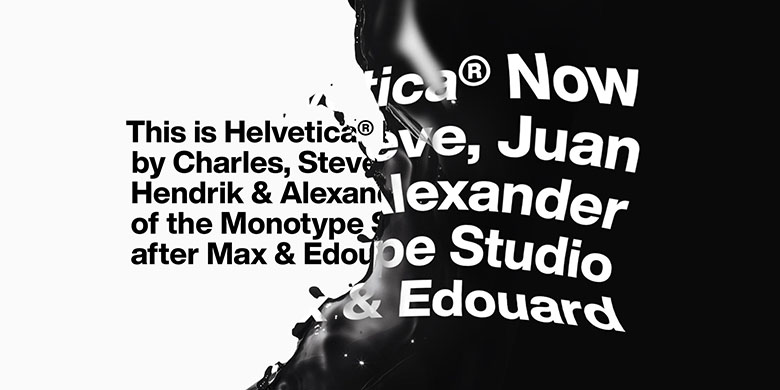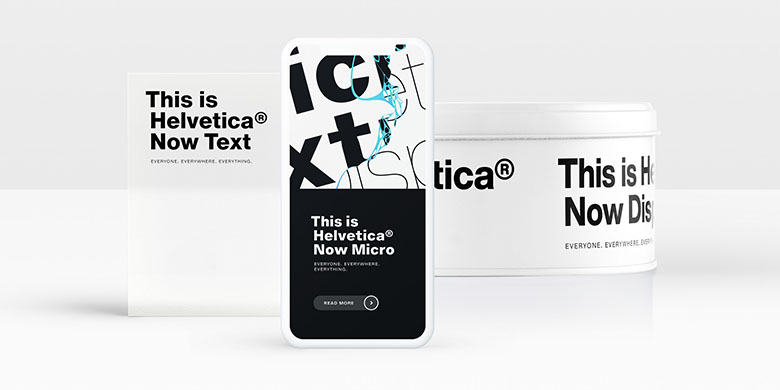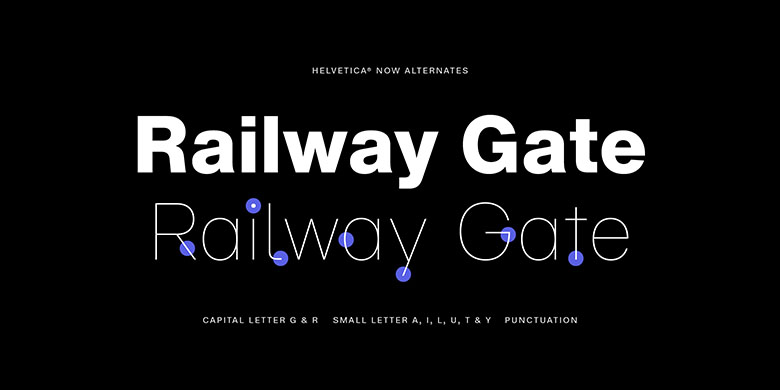
فونت بسیار قدیمی و محبوب «هلوتیکا» بازطراحی و بهروزرسانی شد تا در اندازه و شکلهای متنوع قابل استفاده باشد
هلوتیکا یکی از قدیمیترین فونتها در جهان است که در سال ۱۹۵۷ خلق شد. این فونت محبوبیت بسیار زیادی دارد و گرافیستی نیست که با آن آشنایی نداشته باشد.
هنوز ما این فونت را روی تیشرتها یا برخی تابلوهای راهنمایی و رانندگی، ایستگاههای مترو و غیره میبینیم.
اما فونت هلوتیکا مشکلاتی دارد که باعث میشوند همهجا از آن استفاده نشود. برخی مواقع بسیار ساده است یا برای استفاده روی بنرها و فضاهای بسیار بزرگ چندان مناسب نیست. از سوی دیگر، در فاضهای کوچک از جمله صفحهنمایشها کارکترهای آن اصلا کیفیت لازم را ندارند و ناخوانا هستند. فراموش نکنید که این روزها چقدر ما با صفحههای کوچک کار داریم.
این محدودیتها باعث شدند موسسه Monotype که صاحب فونت هلوتیکا است؛ دو سال گذشته را روی بازطراحی و تغییر و اصلاح حروف و کارکترهای آن صرف کند. نتیجه، فونتی به نام Helvetica Now است که در آستانه گرفتن مجوز و استفاده همگانی است.
فونت Helvetica Now در دو تایپوگرافی طراحی شده است. هنگامی که تمام کارهایی که میشود با این فونت جدید انجام داد را مشاهده کنید؛ پی خواهید برد چرا دو تایپوگرافی از این فونت داریم.
تقریبا فونت Helvetica Now سه نسخه از هلوتیکا به دست میدهد. نسخه «Micro» برای صفحهنمایش و فضاهای کوچک است. نسخه «Display» برای نمایش و بزرگ دیده شدن عبارتها و جملات است و نسخه «Text» نیز بیشتر برای استفاده در اندازه استاندارد فونتها است. هر سه نسخه در فاصله و کشیدگی حروف تفاوتهایی دارند تا خواناتر باشند.
این نسخهها مشکل عدم خوانایی ده ساله فونت هلوتیکا را حل کرده و فاصله کارکترها از هم مناسبتر میشود.
با مراجعه به سایت Helvetica Now میتوانید تغییرات فونت هلوتیکا را در نسخههای جدید مشاهده کنید. به وضوح فاصله حروف از هم، شکستگیهای بیشتر حروف، قوسهای کم و نازک و خوانایی آنها در نمایشهای مختلف بهتر شده است. شما میتوانید در این سایت، فونت جدید را در اندازههای مختلف مشاهده یا خودتان حروف و جملاتی را نوشته و مقایسه کنید.
موسسه Monotype میگوید با نسخههای micro و display و text میتوانید هر چیزی را نوشته و پوشش دهید.
چندین ویرایش در طول تاریخ و اکنون بهترین آنها
Helvetica Now اولین بهروزرسانی بزرگ فونت هلوتیکا نیست. در طول این سالها چندین بار دستخوش تغییرات و دگرگونیهایی شده است. در سال ۱۹۸۳ نسخه دیجیتالی ان به نام Neue Helvetica عرضه شد.
Monotype با ایجاد تغییراتی در Neue Helvetica نسخه جدیدی به نام Helvetica Neue ساخت که برای استفاده کاربران در ابزارهای دیجیتالی مناسب بود. همان فونتی که اپل برای مدت کوتاهی در iOS و MacOS استفاده کرد تا فونت تایپوگرافی San Francisco ساخته شد.
در حقیقت، طی سالهای اخیر شرکتهای زیادی مانند اپل، گوگل، ایربیانبی و حتی کوکاکولا نسخههایی دستکاری و ویرایش شده از فونت هلوتیکا را توسعه دادند که عمدتا یک نسخه مشابه هلوتیکای اصلی بودند.
احتمالا بیشتر از کاربران، طراحان و گرافیستها از نسخههای جدید فونت هلوتیکا استقبال خواهند کرد و با آنها دیوانه میشوند. تغییرات صورت گرفته فقط برای خوانایی بیشتر نیست و زیباشنایی شگفتانگیزی با خود به همراه دارد.
مثلا، به طرز نوشته حروفی مانند «G» یا «U» توجه کنید که بسیار زیباتر از نمونه اصلی هلوتیکا هستند؛ انگار که برای طراحی تایپوگرافیهای هنری ساخته شدند. احتمالا فونت هلوتیکا بیشتر از هر زمان دیگری در طراحیها استفاده شود.